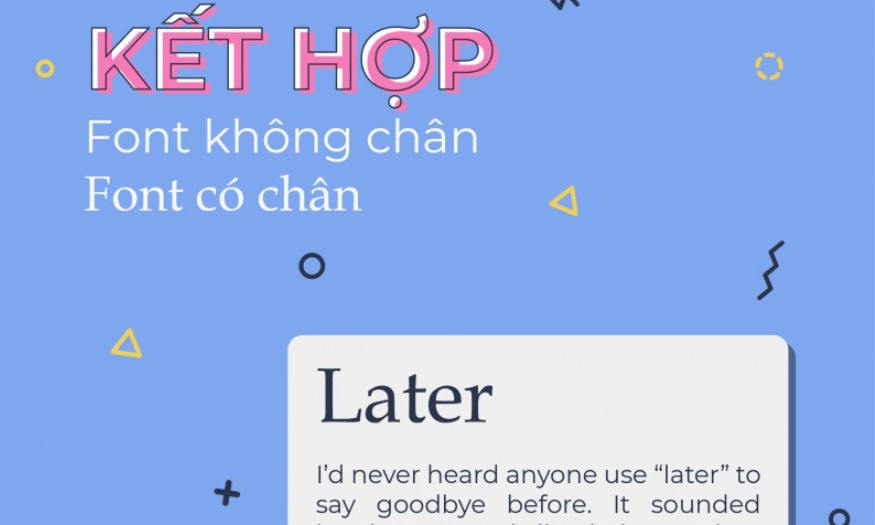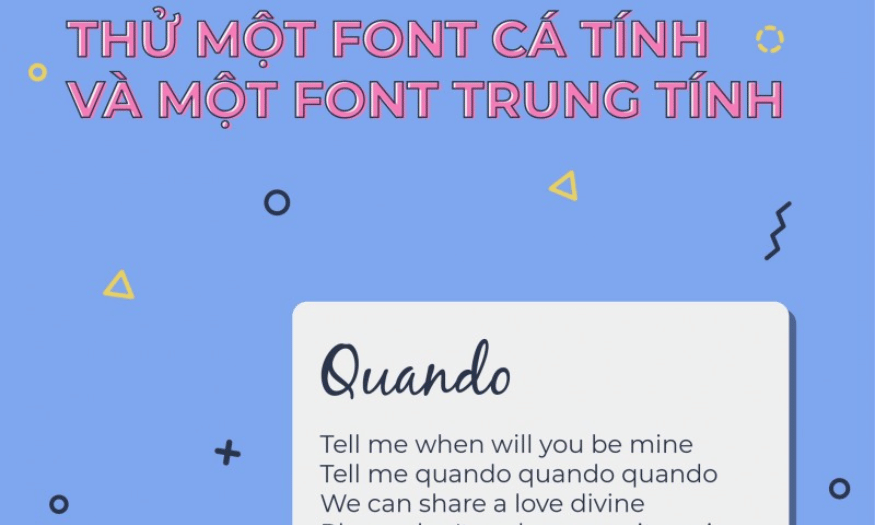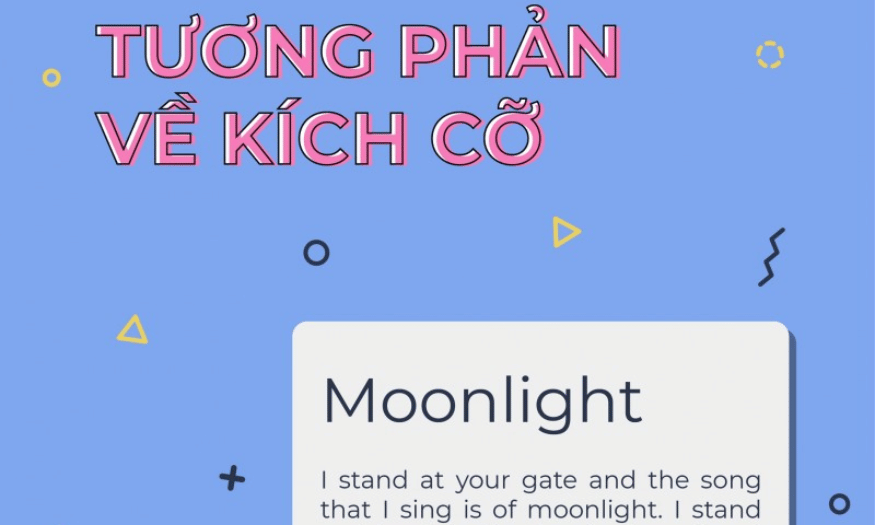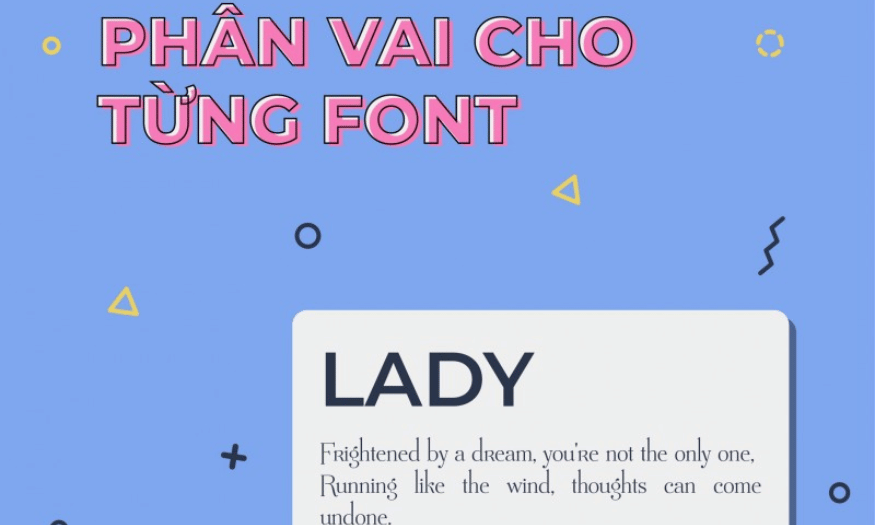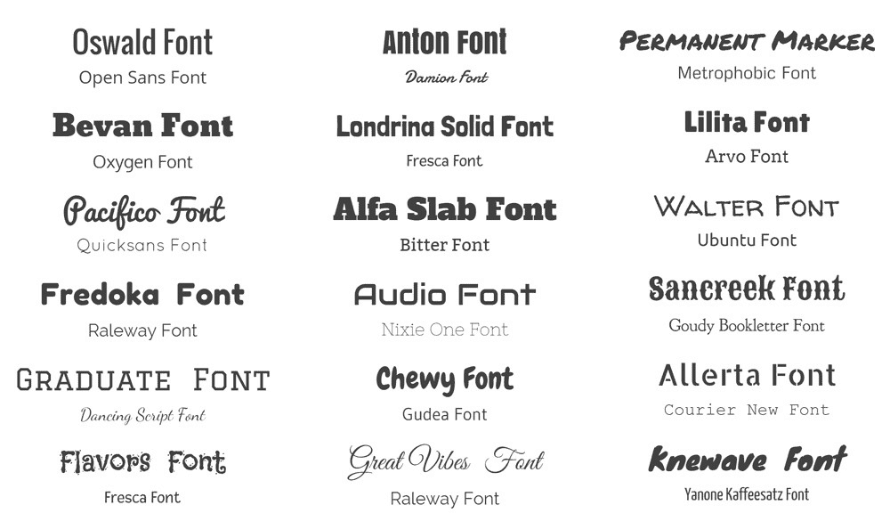
Sử Dụng Font Chữ Đúng Cách, Tạo Nên Thiết Kế Đúng Điệu
Font chữ không chỉ là một phần của văn bản mà nó còn là linh hồn của thiết kế. Việc lựa chọn font chữ phù hợp không chỉ giúp nâng cao tính thẩm mỹ mà còn đảm bảo thông điệp được truyền đạt một cách rõ ràng và hiệu quả. Đặc biệt, trong thiết kế đồ họa, font chữ có thể tạo ra sự khác biệt giữa một sản phẩm nổi bật và một sản phẩm dễ bị lãng quên. Sự kết hợp hài hòa giữa các loại font và cách sử dụng chúng một cách thông minh sẽ giúp thiết kế trở nên chuyên nghiệp và ấn tượng hơn.Hãy cùng Sadesign khám phá cách sử dụng font chữ sao cho phù hợp trong thiết kế.
1. Kết hợp font không chân và một font có chân
Việc kết hợp giữa font chữ không chân (sans serif) và font có chân (serif) là một trong những cách đơn giản nhưng hiệu quả để tạo ra sự tương phản trong thiết kế. Font chữ không chân thường mang đến sự hiện đại, sạch sẽ và dễ đọc, trong khi font có chân lại mang lại cảm giác truyền thống, tinh tế và có chiều sâu. Khi đặt chúng cạnh nhau, mỗi loại font sẽ làm nổi bật những đặc điểm riêng của nhau, tạo cảm giác hài hòa và hấp dẫn.
Tuy nhiên, điều quan trọng là không nên chọn bừa bãi. Không phải mọi cặp font chữ cùng loại này sẽ hòa hợp với nhau. Sự tương phản quá mạnh có thể dẫn đến cảm giác “bất hòa”, làm giảm đi tính thẩm mỹ của thiết kế. Vì vậy, hãy cân nhắc kỹ lưỡng và thử nghiệm với nhiều lựa chọn để tìm ra sự kết hợp tốt nhất cho dự án của bạn.
2. Thử 2 font cùng một họ
Một cách hiệu quả khác là sử dụng hai font chữ khác nhau từ cùng một họ. Điều này đem lại sự đồng nhất và hài hòa, giúp bạn tiết kiệm thời gian mà vẫn đảm bảo tính thẩm mỹ. Các font cùng một họ thường có những đặc điểm thiết kế tương tự, vì vậy chúng dễ dàng phối hợp và tạo ra cảm giác thống nhất trong toàn bộ thiết kế.
Để tạo ra sự tương phản cần thiết, bạn có thể điều chỉnh kích thước, độ đậm hoặc sử dụng các hiệu ứng nổi bật cho các phần văn bản quan trọng. Điều này không chỉ giúp thu hút sự chú ý mà còn làm nổi bật thông điệp bạn muốn truyền tải. Sự khéo léo trong việc lựa chọn và điều chỉnh sẽ mang lại cho thiết kế của bạn một diện mạo chuyên nghiệp và ấn tượng.
3. Thử một font cá tính với một font trung tính
Khi bạn đã quyết định sử dụng một font chữ có phong cách cá tính và ấn tượng, hãy cẩn thận khi lựa chọn font chữ còn lại. Nếu cả hai đều mang tính chất nổi bật, chúng có thể “cạnh tranh” lẫn nhau, dẫn đến sự hỗn loạn trong thiết kế. Một thiết kế tốt cần có sự phân cấp rõ ràng, và điều này chỉ có thể đạt được khi một font giữ vai trò chính và font còn lại hỗ trợ một cách nhẹ nhàng.
Giống như câu nói “một núi không thể có hai hổ”, hãy để cho mỗi font chữ có không gian và vai trò riêng của nó. Sự tương phản giữa một font cá tính và một font trung tính sẽ mang lại sự cân bằng và giúp người xem dễ dàng tiếp nhận thông tin hơn. Điều này không chỉ làm tăng tính thẩm mỹ mà còn cải thiện khả năng truyền tải thông điệp.
4. Tránh 2 font “trái tính”
Khi kết hợp các font chữ, điều đặc biệt quan trọng là tránh việc sử dụng hai font có phong cách trái ngược hoàn toàn. Mỗi font chữ đều mang lại cảm xúc và thông điệp riêng, vì vậy việc lựa chọn những font có tính chất quá khác biệt có thể khiến thiết kế trở nên lộn xộn và không đồng điệu.
Ví dụ, một font chữ như Rush Slab Black Shadow với hình khối mạnh mẽ, cứng cáp sẽ không hòa hợp với một font chữ như Boli Regular, vốn trẻ trung và vui tươi. Sự kết hợp này không chỉ làm giảm đi tính thẩm mỹ mà còn gây khó khăn cho người xem trong việc tiếp nhận thông tin. Việc lựa chọn font chữ cần sự tinh tế và cân nhắc để đảm bảo rằng chúng hỗ trợ lẫn nhau và tạo ra một tổng thể hài hòa, hấp dẫn.
5. Tương phản về kích cỡ
Một trong những cách hiệu quả nhất để tạo ra sự tương phản trong thiết kế là thay đổi kích thước font chữ. Chính quy luật trực quan “lớn hơn thì hút hơn” giúp dẫn dắt ánh nhìn của người xem. Khi người đọc nhìn vào một thiết kế, họ thường bị thu hút bởi những chi tiết lớn trước, như tiêu đề hay các phần nổi bật khác. Điều này không chỉ tạo ra sự chú ý mà còn giúp phân cấp thông tin một cách rõ ràng và logic.
Sự phân cấp này rất quan trọng, bởi vì nó giúp người xem dễ dàng nhận diện cấu trúc nội dung. Ví dụ, một tiêu đề lớn và nổi bật sẽ thu hút sự chú ý ngay lập tức, trong khi các đoạn văn bản nhỏ hơn sẽ hỗ trợ thông tin bổ sung mà không làm mất đi sự chú ý vào phần chính. Điều này tạo ra một trải nghiệm đọc mạch lạc và dễ dàng hơn cho người xem.
Cuối cùng, khi sử dụng kích thước font chữ để tạo sự tương phản, bạn cần chú ý đến sự hài hòa. Một thiết kế có quá nhiều kích thước khác nhau có thể khiến người xem cảm thấy rối mắt. Hãy chọn lựa một vài kích thước chính để tạo ra sự cân bằng giữa sự nổi bật và sự nhất quán trong toàn bộ thiết kế.
15. Kết luận
Tóm lại, việc sử dụng font chữ đúng cách là một yếu tố then chốt trong thiết kế. Nó không chỉ giúp tăng cường khả năng truyền tải thông điệp mà còn tạo ra ấn tượng đầu tiên mạnh mẽ cho người xem. Một thiết kế đẹp không chỉ dựa vào hình ảnh mà còn phụ thuộc rất lớn vào cách lựa chọn và sử dụng font chữ. Bằng cách nắm vững nguyên tắc này, bạn có thể tạo ra những tác phẩm thiết kế không chỉ bắt mắt mà còn mang tính chuyên nghiệp, góp phần làm nổi bật thương hiệu và thông điệp mà bạn muốn truyền tải.